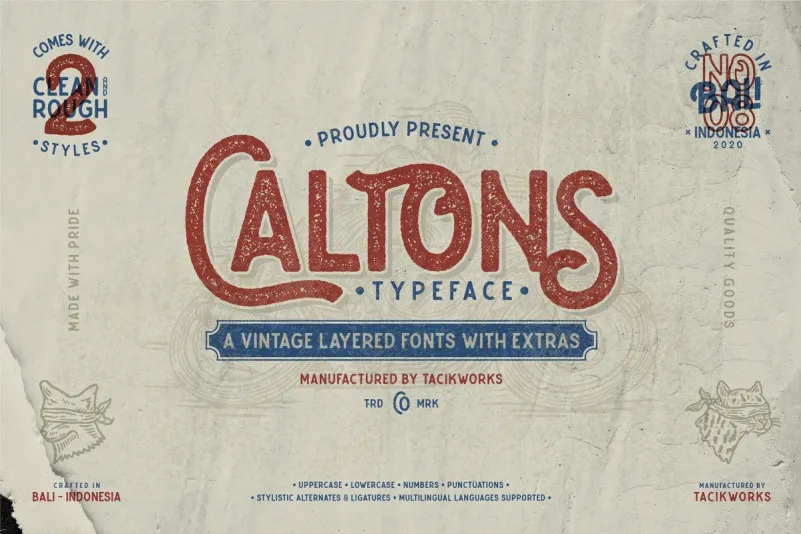
Caltons Font
A Caltons Font é uma fonte para exibição desenvolvida por Tacikworks, inspirada nos designs vintage com linhas limpas e grossas. Com aproximadamente 600 caracteres gílios, incluindo maiúsculas e minúsculas, ligaturas apropriadas e ligações alternativas, ela permite um visual clássico que destaca-se ainda mais. Perfeita para criação de designs vintage como logomarcas, materiais promocionais, roupas, folders e cartões de visita, a Caltons Font é uma escolha ideal para designers atentos aos detalhes. Seja você um artista digital ou designer gráfico buscando inspiração vintage, esta fonte certamente se encaixa no seu estilo criativo.